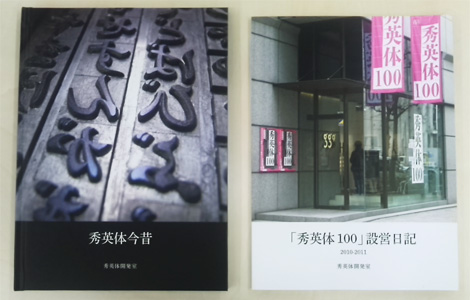
秀英体のコネタ
第34回 「DNPのフォトブック」でこだわりのフォトブックづくりをしませんか?
みなさんはフォトブックを作ったことはありますか?
最近、フォトブックを手軽に作成できるサービスがたくさんありますよね。DNPにも「ドリームページ」や「ドリームページ・プラス」などのフォトブック作成サービスがあるのをご存知でしょうか?実は、「ドリームページ」では秀英体フォントを使えるんですよ!
「ドリームページ」&「ドリームページ・プラス」でつくったフォトブックたち
秀英体もご縁のある「ドリームページ」&「ドリームページ・プラス」の特徴や作例について、DNPのフォトブックの広報を担当している、情報記録材事業部 事業推進本部 マーケティング室の犬束さんに、お話を聞いてきました。
――さっそくですが、DNPのフォトブック作成サービスにはどのようなものがあるか教えてください。
犬束:パソコンの専用アプリを使い自由に編集注文できるのが「ドリームページ・プラス」
、 ウェブブラウザから手軽に編集注文できるのが「ドリームページ」
家電量販店などのセルフプリント機で短時間(最短5分)でフォトブックを作れる「プリントラッシュ フォトブック」
と3種類のサービスを提供しています。
これらを総称して「DNPのフォトブック」と呼んでます。昨年11月末にウェブサイトも公開しました。
大日本印刷グループのフォトブック作成サイト「DNPのフォトブック」
まとめて紹介したほうが分かりやすいよねというのと、社名とサービス内容のフォトブックを冠することで、お客様への信頼に訴求できるように、と思っています。
最高レベルの品質をお手頃価格で
――いまフォトブックのサービスってたくさんありますよね。比較サイトもあるみたいです。「ドリームページ」&「ドリームページ・プラス」(以下、あわせて「ドリペ」)のアピールポイントを教えてください。
犬束:「ドリペ」の品質は、今あるフォトブック作成サービスの中で最高レベルとの自負があります。また、価格は高品質なのにお手頃に抑えています。
――私も数回フォトブックを作成したことがありますが、「ドリペ」のプリント品質は以前より良くなっていますよね。
犬束:プリンターを高品質な「6色印刷」に変えて、「仕上がり(グロス、マット、ナチュラル)」を選べるように工夫しました。それ以外にも、お客様の要望やトレンドに併せて、カラープロファイル(写真のデータをどういった色合いでプリントするかの設定)は日々チューニングをしているんですよ。
6色印刷は、他社にも別料金で選べるところはあるのですが、「ドリペ」では4色印刷並みの価格のままで提供しています。
通常のカラー印刷は4色です。
6色は4色よりもクリアーで鮮やかな発色、滑らかな階調でプリントできます。
犬束:「仕上がり」を選択できる機能では、つやつやしたグロス、おちついた印象のマット、素朴な風合いのナチュラルから作品の仕上がりを選べます。こういった仕上げ加工を選べるのは「ドリペ」だけなんです!
マットとナチュラルが分かりにくいとみんなに言われるんですが・・・手触りが違ったり、マットは明るく白っぽく、ナチュラルは生成りのやさしい質感です。いま、紙のトレンドとして、ムック本などにもナチュラルな紙が使われています。こういった流行りの紙とか、印刷だけじゃなくて最終的な仕上げ加工まで選べるのが、「ドリペ」の特徴です。
左からグロス、マット、ナチュラル
マットとナチュラル、確かに画面越しだと区別がつきませんが、
紙の質感が違うので手元で見るとけっこう雰囲気が違います。
――せっかくの質感の違いが、画面越しでは伝わりにくいのがもったいないですね・・・
犬束:市谷のドットDNP
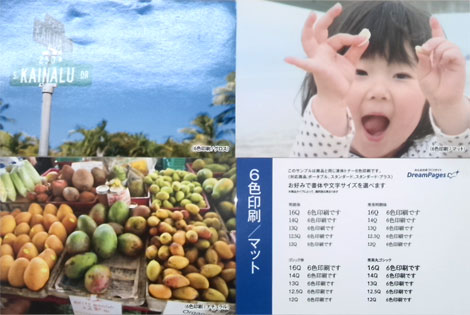
カード状のサンプル。写真の色合いや用紙の質感を確認できます。(書体見本もついています!)
犬束:また、プリント方法は6色印刷のほかに、昇華型熱転写方式(写真プリント)の「フォトプレミアム」も提供しています。写真のセルフプリント機と同じ、写真品質の鮮やかな発色やツヤでプリントできます。標準のプリントよりは高価格ですが、特別なアルバムをお求めの方に使っていただいています。
フォトブックの意外な使い方
――「ドリペ」ではどのようなテーマのフォトブックが作られていますか?
犬束:写真プリントと同じで、やはり、家族・子供・ウェディングをテーマとしたフォトブックが多いです。
家族やお子さんのフォトブックを作りたいお客様の多くは、家事に育児に忙しく、手軽に作りたいという方が多いので、より手軽にフォトブックを作れるように、「ドリームページ・プラス」には写真を自動でレイアウトする「簡単フォトブック」という商品メニューがあります。
それ以外では、趣味にフォトブックを活用されるお客様も増えてきています。写真が趣味の方だけでなく、レシピ本、ハンドメイド品のカタログ、画集、華道の作品集なども作られています。お祖母様の描いた水彩画をお孫さんがフォトブックにまとめて、お祖母様のお誕生日プレゼントにするという例もありました。
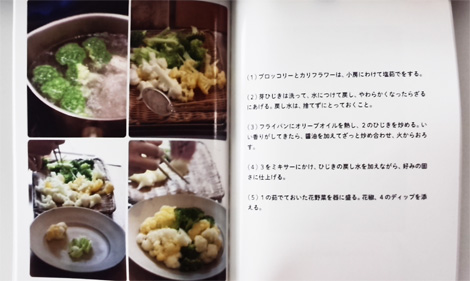
テキストもたっぷり入力できるので、レシピ本もつくれます。
――レシピ本や画集など、フォトブックという枠に収まらない使い方もアリなんですね。
犬束:詩集など写真よりも文字メインの作品もあります。もともと自費出版に興味のある方が、手軽に1冊から作れるということで、フォトブックを使われることもあるようです。
「ドリームページ」のウェブサイトに作品を公開できるギャラリーページがありますが、作品テーマとして「詩・エッセイ」というタグがあるんですよ。
――本当ですね!絵本や雑誌風の作品など、バラエティー豊かな作品があります。
犬束:ユニークな使い方としては、伝記みたいな作品を作られる方もけっこう居らっしゃいます。例えば、モチーフになる方の親族が、業績や経歴などを1冊にまとめるというものです。全国的には著名でなくても、地域や業界では知られている方について、周囲の方の記録に残したいという思いからまとめられるみたいで。パーソナルな歴史本というか、良い文化だと思います。レイアウトの自由度が高く、写真だけでなく文字も使える「ドリペ」ならではですね。
――お客様の発想で、意外な使い方もされるのが面白いですね。
犬束:以前、アート系の学生さんのフォトブックを展示するイベントを開催したことがありますが、若い人の発想や情熱的な作品はどれも面白かったです!
写真をプリントする機会が減っているイメージがあると思いますが、年配の方はプリントして記録に残す重要性を理解されていますし、若い方たちは逆に、プリントをする発想が無かったのが、プリントの面白さに気づき始めていて、今またプリントの良さが見直されてきていてます。
フォトブックは編集に手間がかかりますが、「作るのは時間がかかって大変だったけど良いものができた!」と思ってもらえるように、お客様に楽しんでもらうために、どう演出するか考えています。
「ドリペ」と秀英体
――ところで、ウェブブラウザ版の「ドリームページ」では秀英明朝と秀英丸ゴシックなどの書体を使えますが、お客様の反応はいかがですか。
犬束:一般のお客様で秀英体を知っている人はほとんど居らっしゃらないですよね(笑)それでも、ワークショップなどで「この書体いいですね」って感想をいただくことがあります。
実際の使われ方を集計しているわけではないのですが、ギャラリーページなどを見ていると秀英丸ゴシックは女性から人気のようです。優しさや柔らかさを表現するのに優れているのかなと思います。
――こういったサービスで選べる書体はゴシックか明朝の2択が多いので、丸ゴシックは珍しいのかもしれません。プロの印刷物と同じ書体を一般のお客様に使っていただけるという形で、秀英体も「ドリームページ」の品質向上に貢献できているのかなと思います。
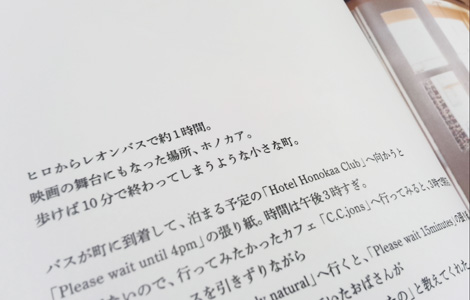
秀英明朝:文芸書などプロの印刷物と同じ書体です!
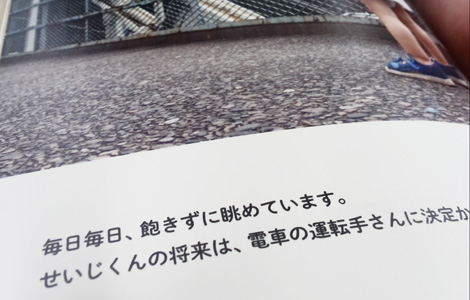
秀英丸ゴシック:優しい雰囲気がお子さんやペットのフォトブックにぴったり
――昨年11月末にオープンした「DNPのフォトブック」「ドリームページプラス」のウェブサイトでは、秀英丸ゴシックのウェブフォントを全面的に使っていただいています。
ウェブフォントとは、ウェブサイトのテキスト表示に、インターネットからフォントを配信する技術です。従来、ウェブサイトのテキストはパソコンやスマフォなどにあらかじめ搭載されている標準的なフォントで表示するのが一般的でした。ウェブフォントを使うことで、印刷物と同じようにバラエティ豊かなフォントで表示できるようになります。今回の秀英丸ゴシックは株式会社リアルタイプ
のウェブフォント配信技術を用いています。
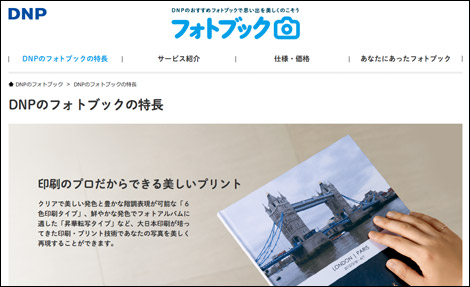
「DNPのフォトブック」のウェブサイト(ウェブフォントのON/OFFを比べる
)
犬束:はじめウェブフォントという案が出てきた時は、SEO的なメリット(※)を考えていたんです。(※ウェブフォントを使うことで、タイトルなども画像を使わずテキストのままデザインができるので検索性が保てます)
「ドリームページ・プラス」は専用アプリをダウンロードしなくてはならないので、サービスの印象を明るく親しみやすい感じで演出したくて、ロゴの色も「ドリームページ」より明るい淡い水色にしています。それで、メインの書体をどうしようという時に、明るく柔らかいイメージで、DNPのフォントということもあるし、秀英丸ゴシックしかないでしょう!と決まりました。
最後に秀英体開発室が作ったフォトブックをご紹介します。活版印刷の現場の写真集『秀英体今昔』
と、2010年の展覧会の記録『「秀英体100」設営日誌』です。(もちろん使用書体は秀英明朝!)